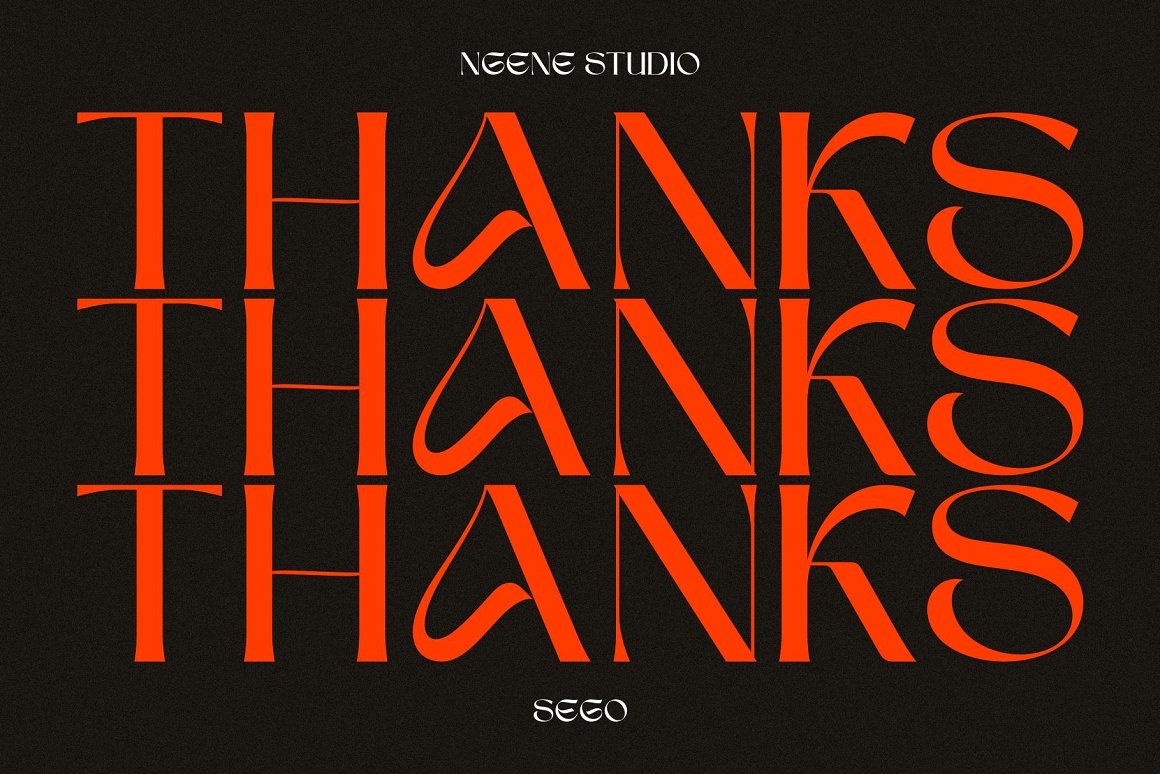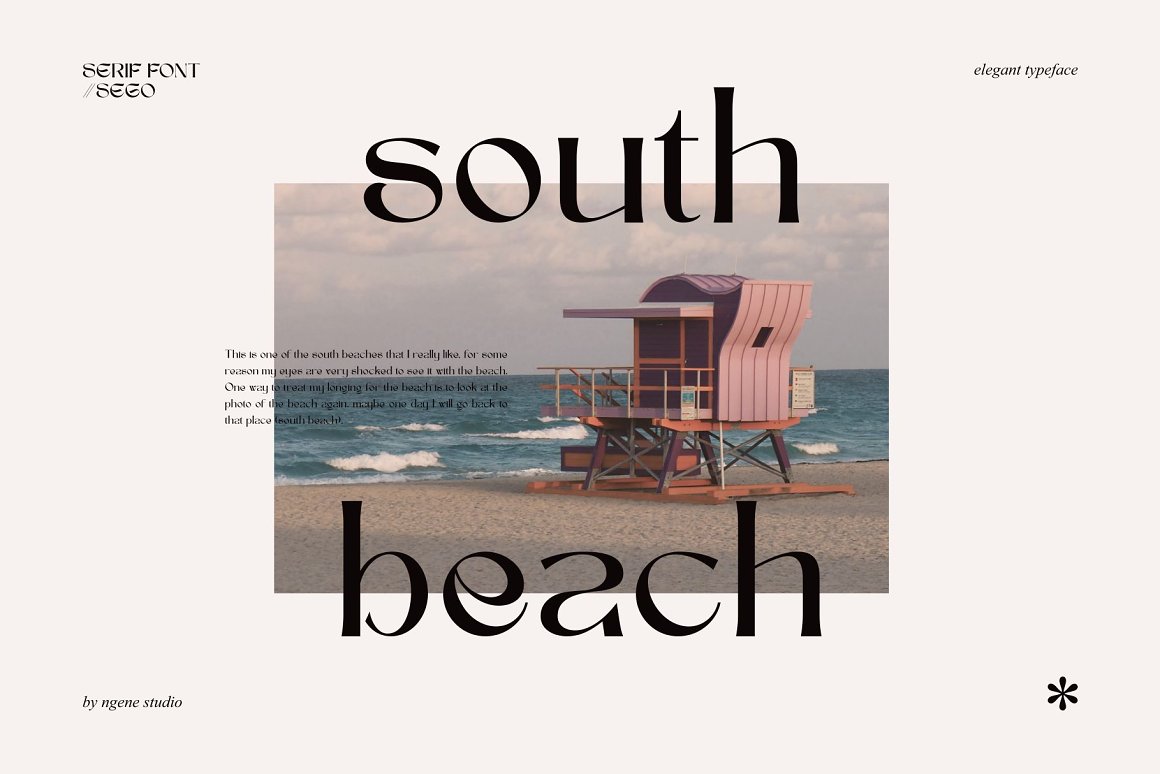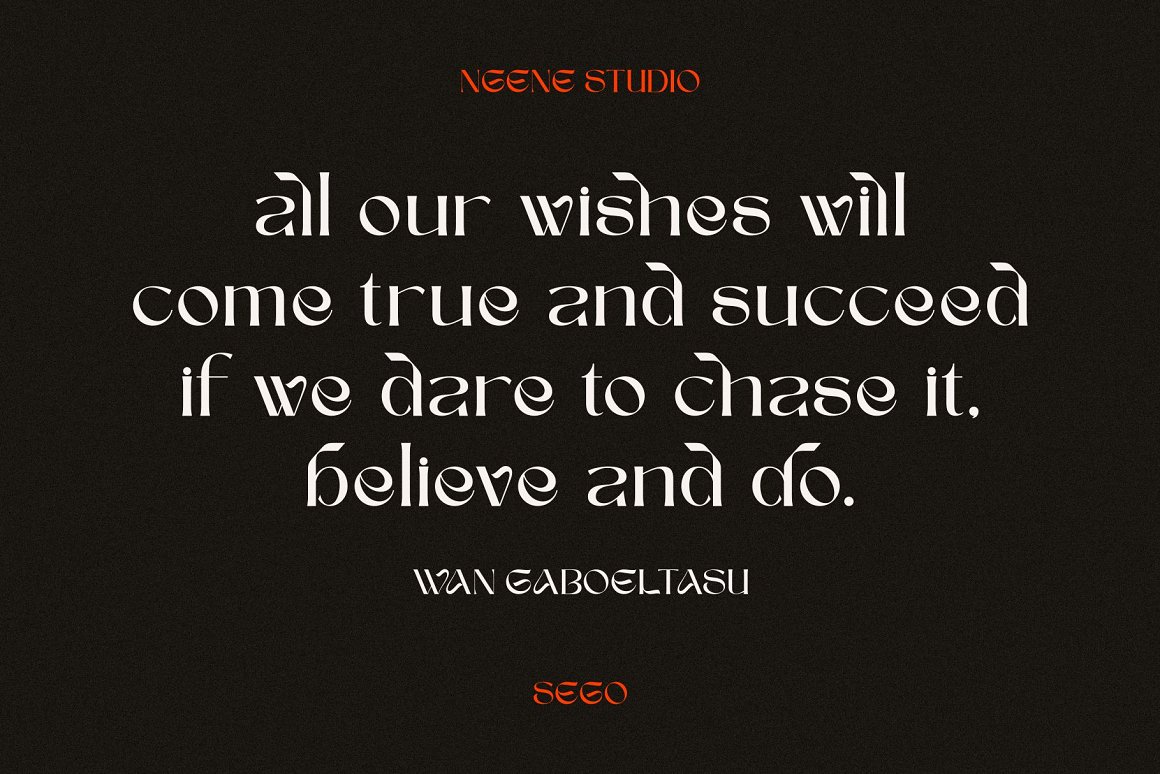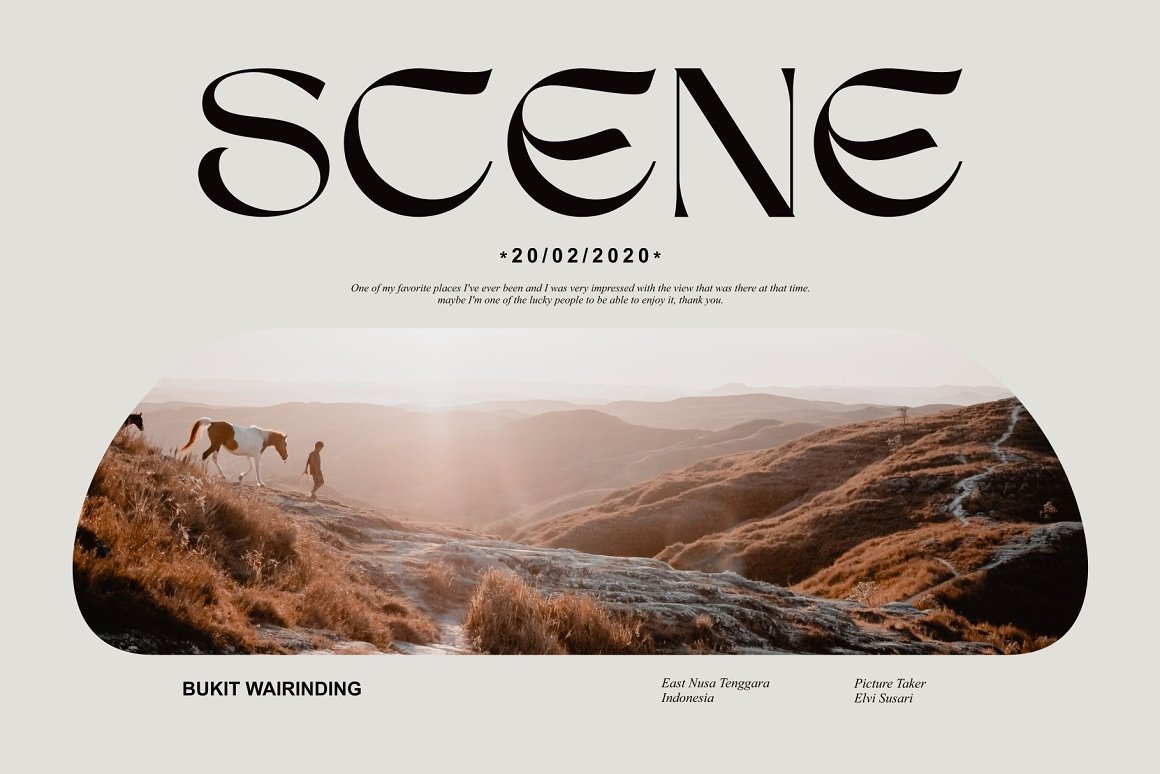
Sego Serif Font
Police serif de style vintage Sego avec une touche élégante et moderne, cette police est étonnante avec différents caractères. Cette police propose plusieurs alternatives, adaptées à la création de logos, de badges, de polices Web, de magazines et autres. Avec une police de caractère très forte, elle rendra votre design différent et plus attrayant.